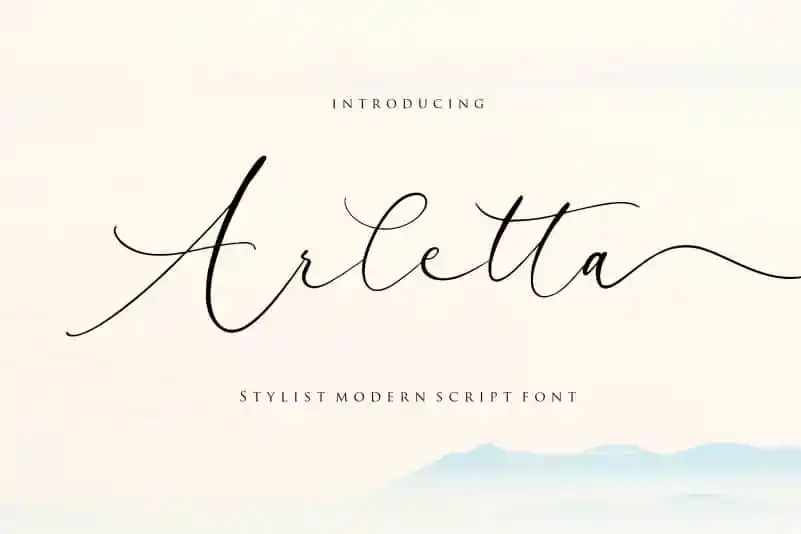
Arletta Script Font – Download Grátis
A fonte Arletta Script é perfeita para aqueles que buscam uma mistura única e divertida de estilos. Seja para aplicar em embalagens de produtos, projetos de marca ou publicações, a sua letra fluida cai como uma luva em qualquer projeto. Suas curvas elegantes e movimento suave fazem dela uma escolha ideal para expressar mensagens sobre o perfil do produto ou projeto. Seja ela usada em revistas modernas ou postagens nas redes sociais, Arletta Script proporciona um toque agradável e inovador ao seu design. Não importa se é usado para destacar palavras sobre backgrounds vibrantes ou de cor neutra – a Arletta Script consegue se encaixar em qualquer ambientes de forma natural e envolvente, tornando-a uma escolha versátil tanto para projetos profissionais quanto pessoais. Como designer de balpirick, criou uma font que é tanto funcional como divertida, tornando-a perfeita para um range amplo de aplicações.